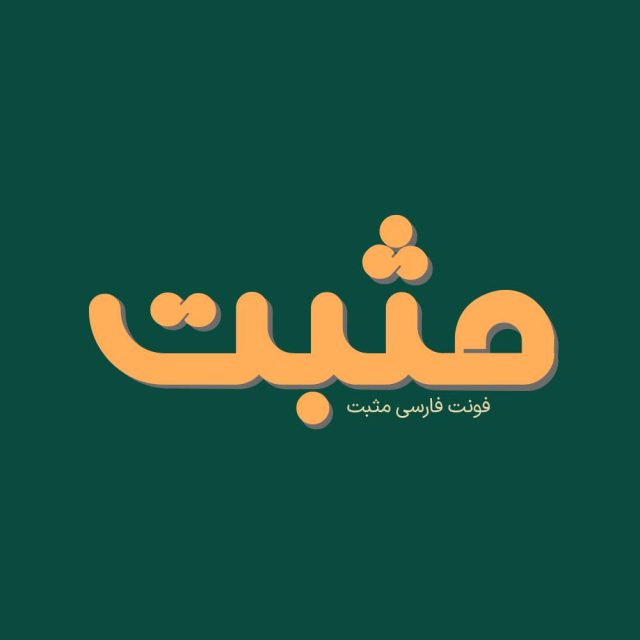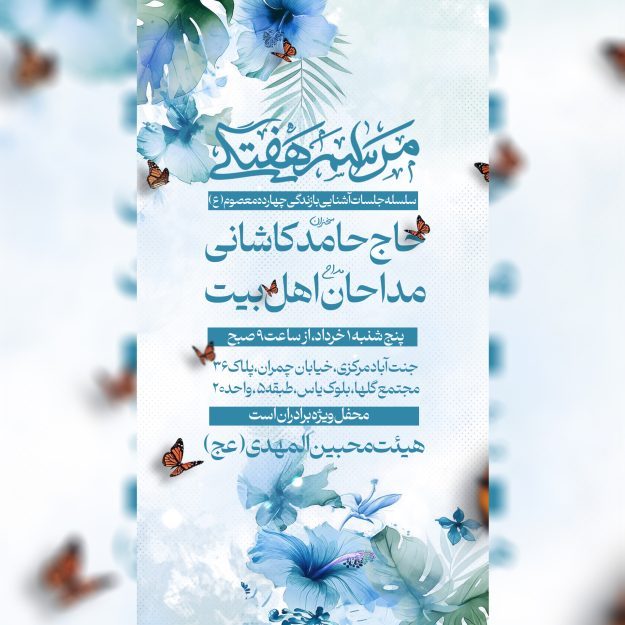
فونت فارسی مثبت Mosbat Font
فونت فارسی مثبت با استفاده از دوایر و زوایای زیبای ریاضی طراحی شده است. در طراحی این فونت سعی شده تا اندازه کافی همه چیز متناسب باشد. نظم کلی حاکم بر فونت بر زیبایی این فونت اضافه می کند. در طراحی این فونت سعی شده سایزها به خوبی نمایش داده شود، شما می توانید به کمک فونت فارسی مثبت لوگوتایپ، تایپوگرافی و طراحی های زیبایی را انجام دهید.
همچنین از این فونت در طراحی تابلوهای چلنیوم هم به دلیل ساختار منحصر به فردش می توانید استفاده کنید. در ادامه برای شما نمونه تایپ های این محصول حرفه ای رو آماده کردیم که میتونید مشاهده کنید.
پیشنمایش و نمونه تایپ های فونت مثبت